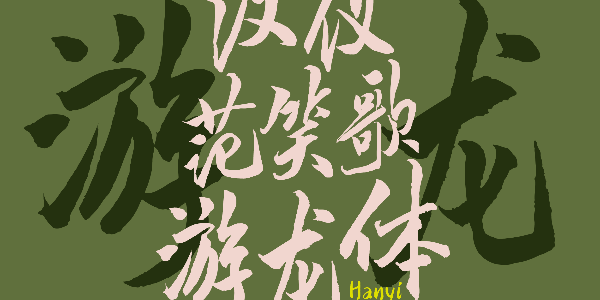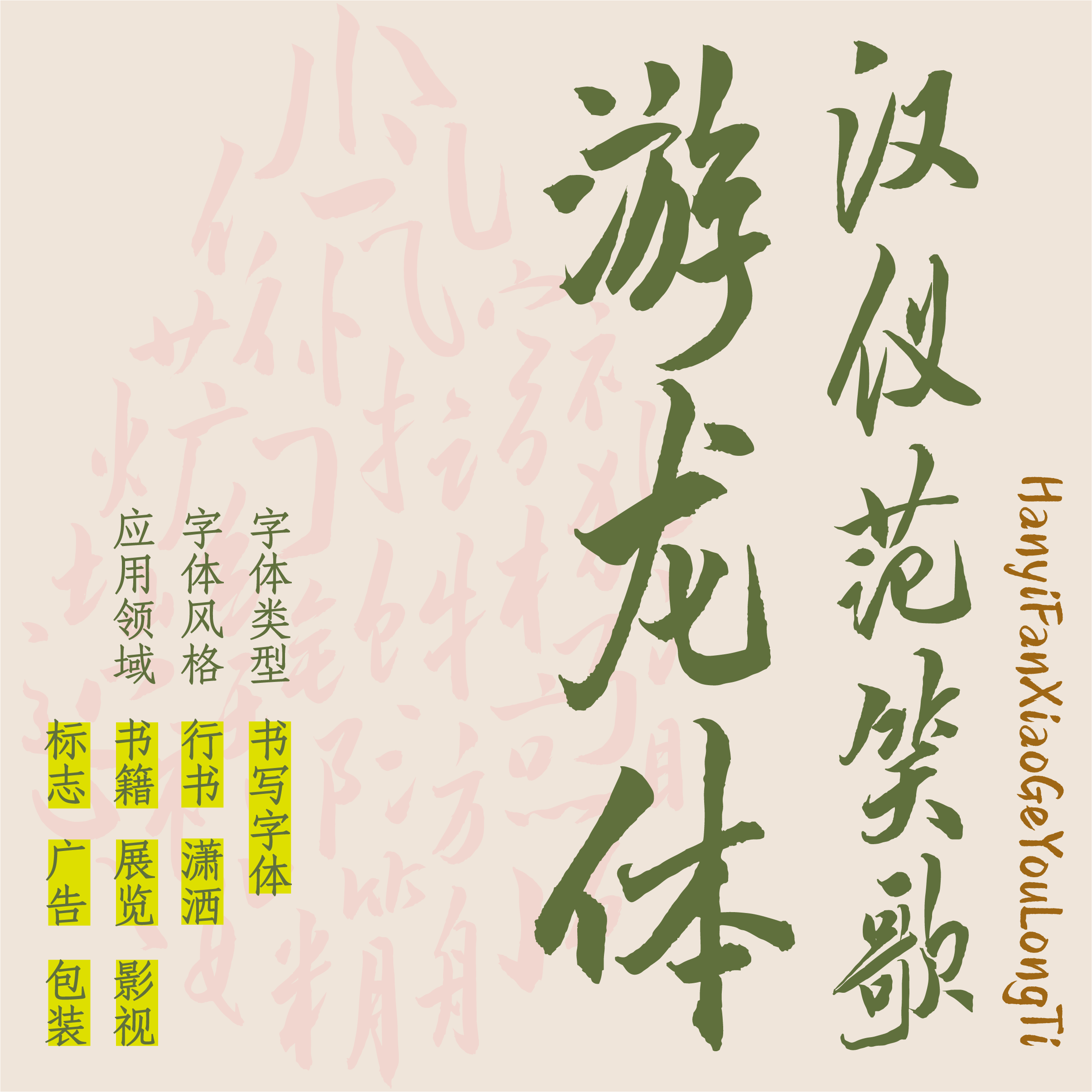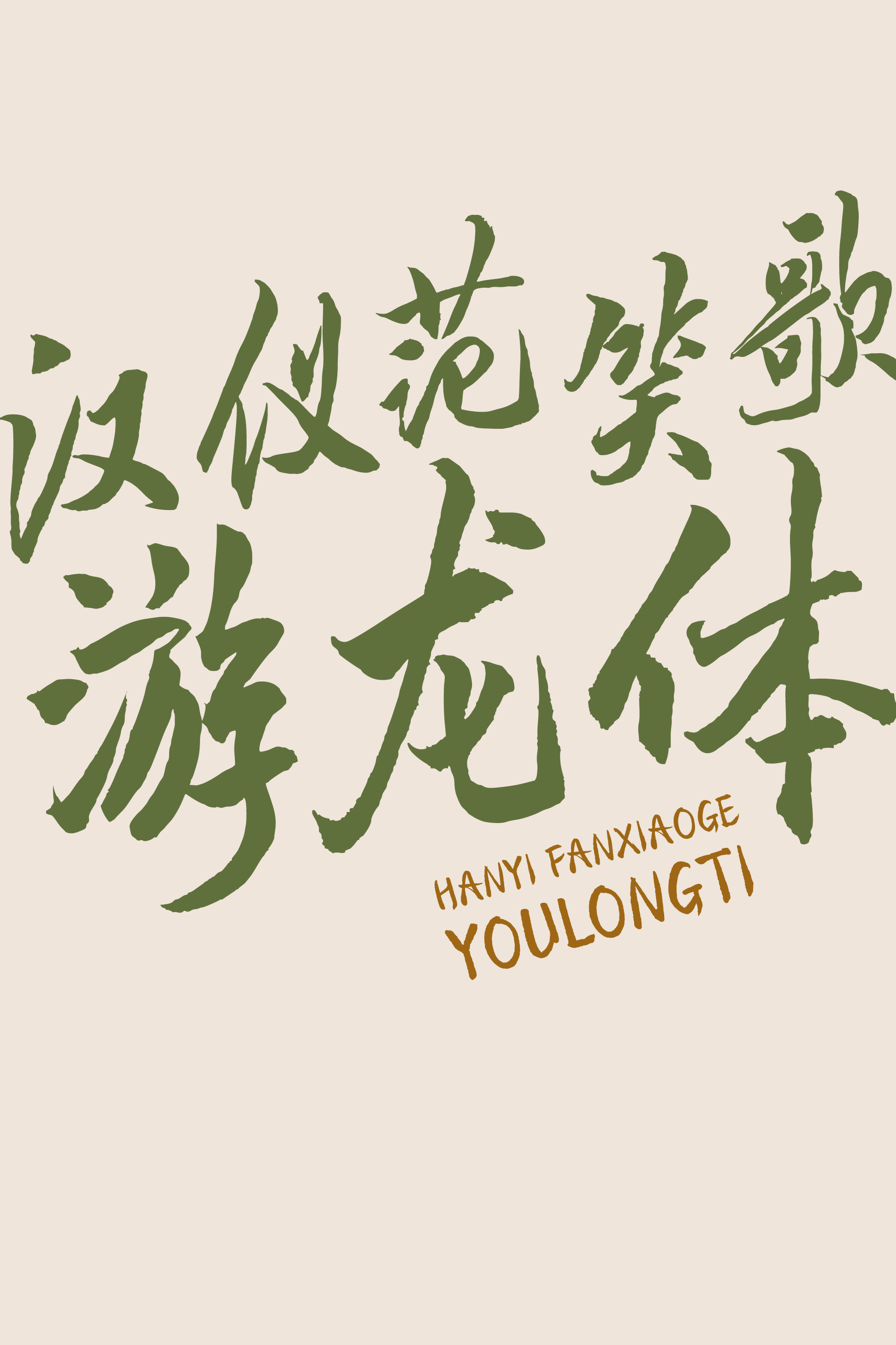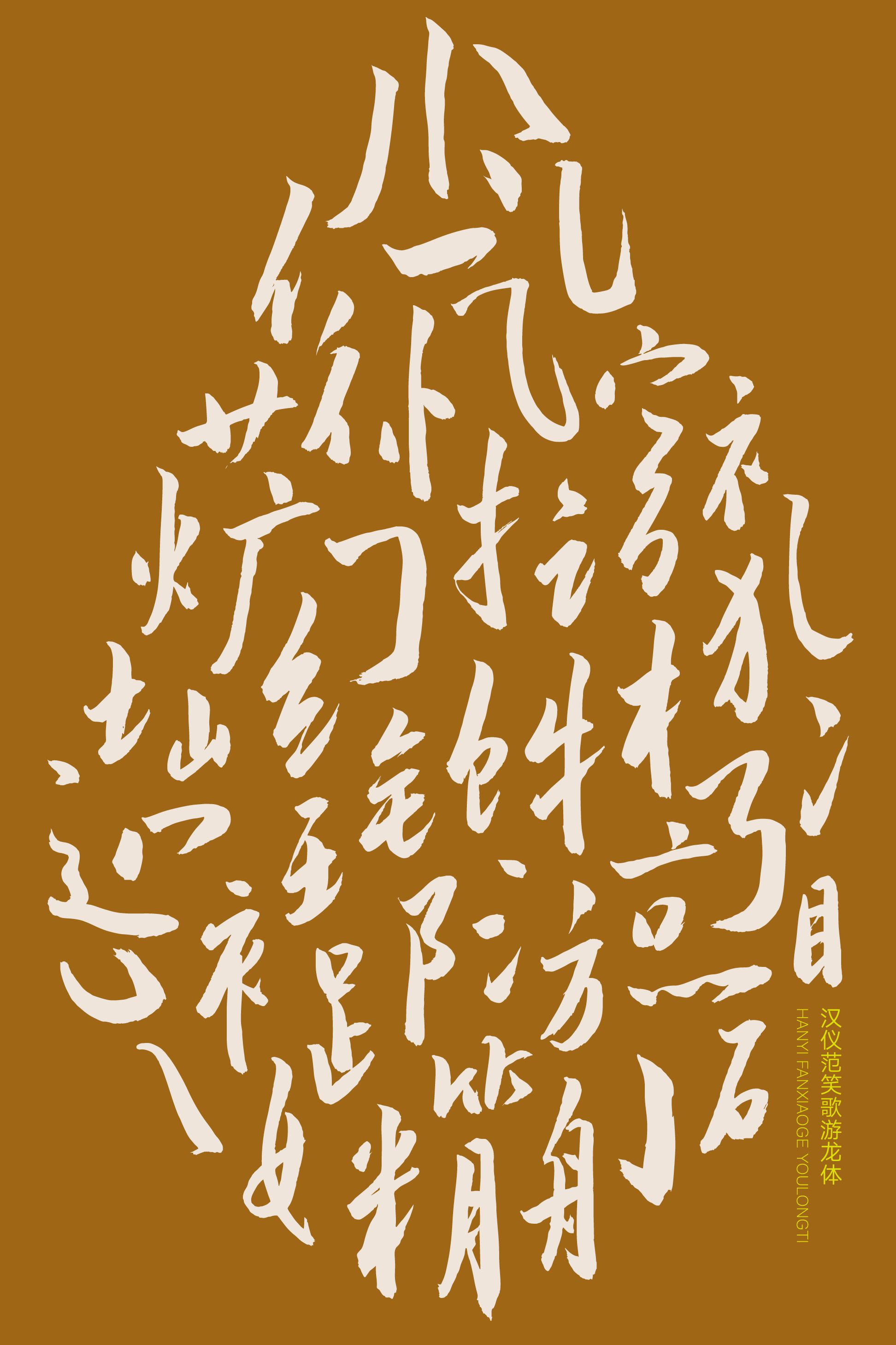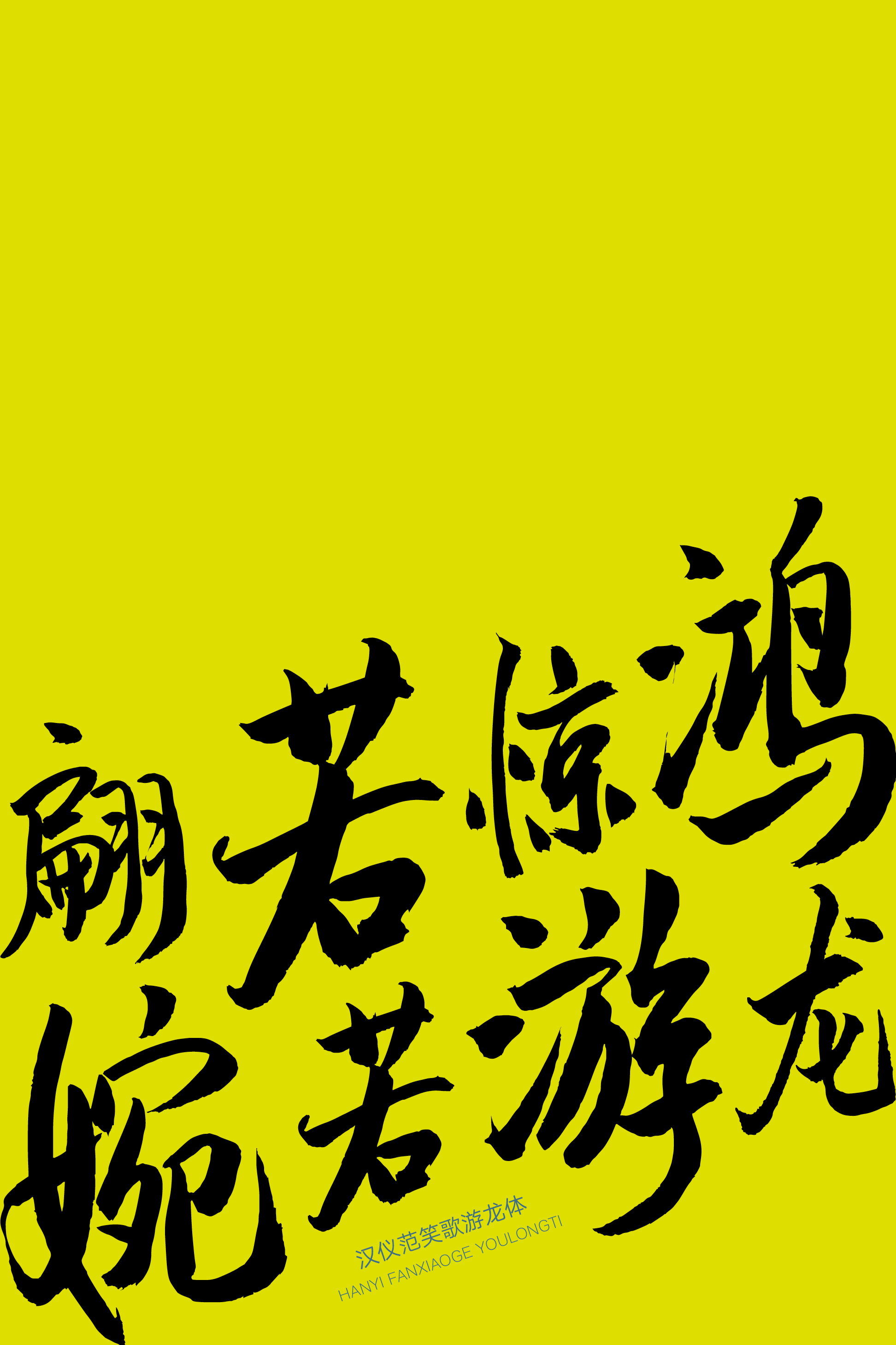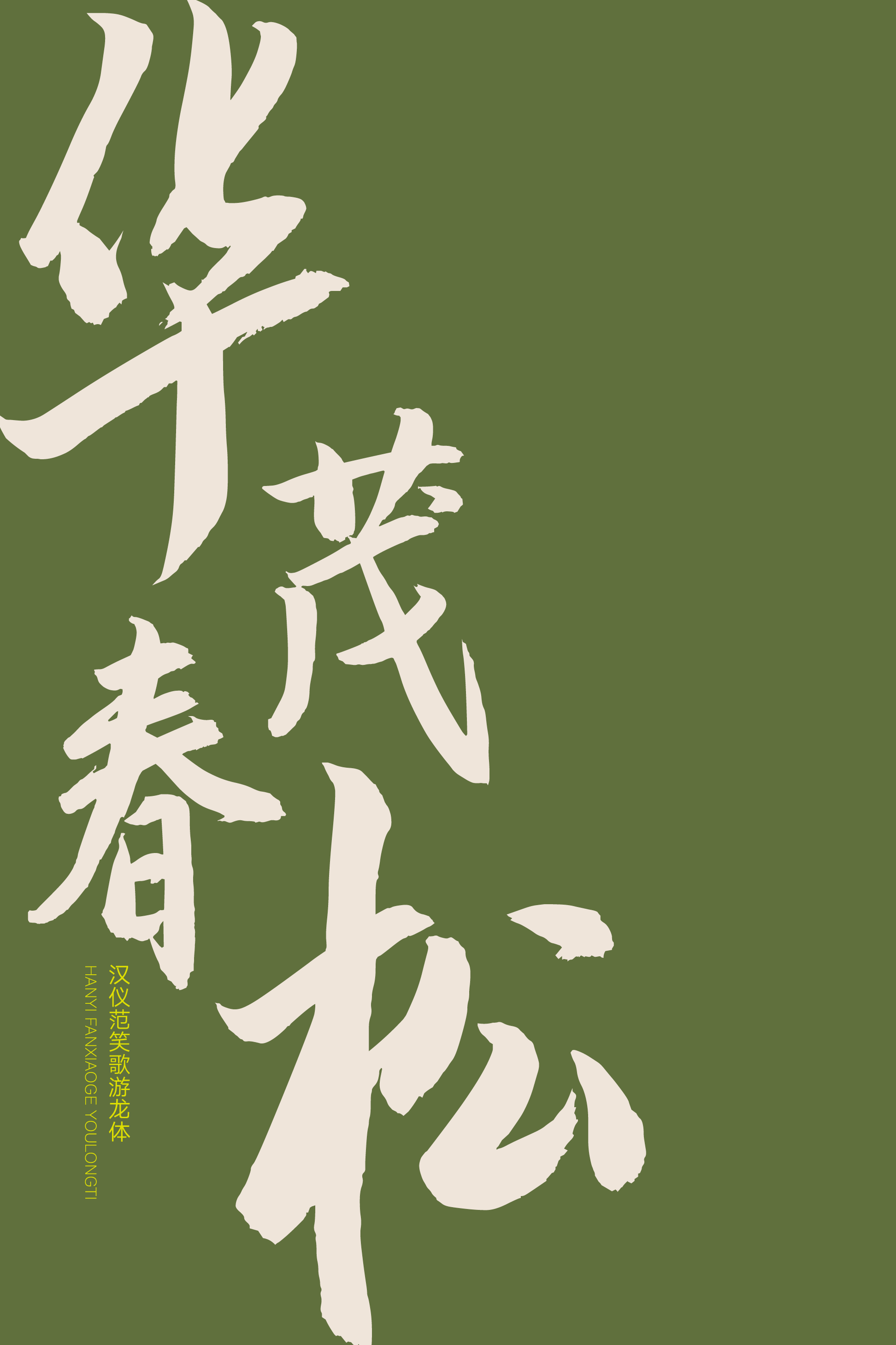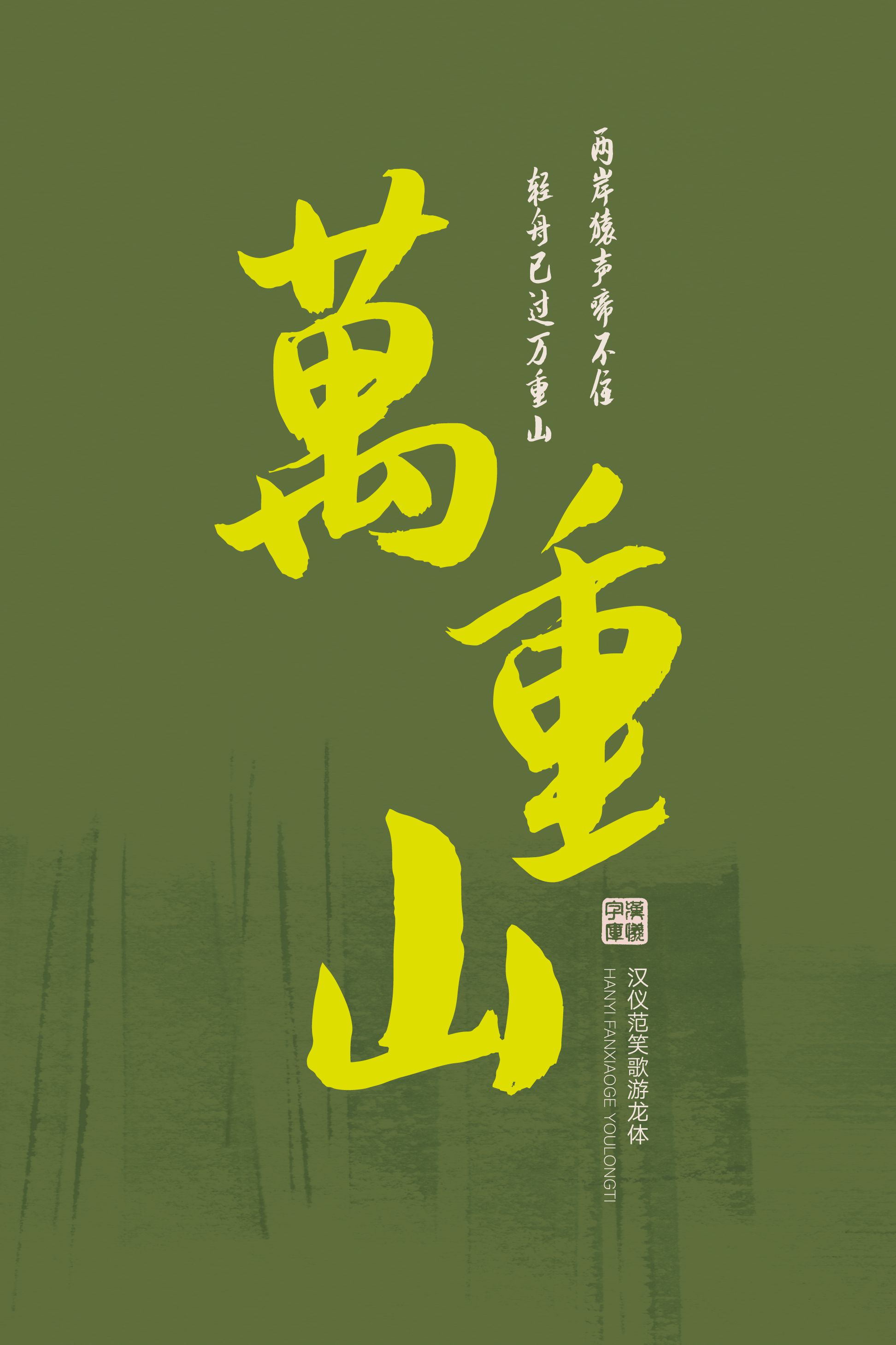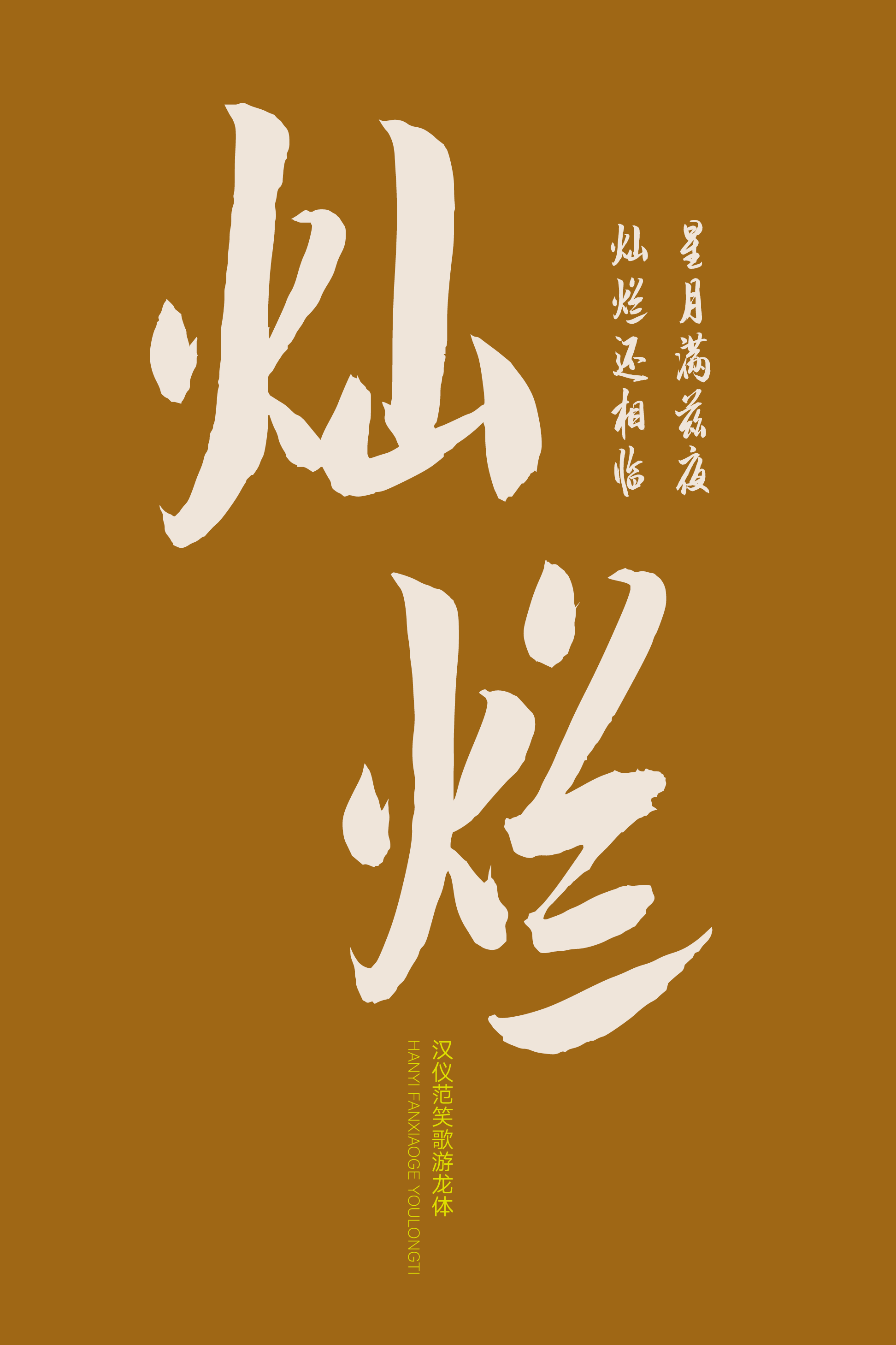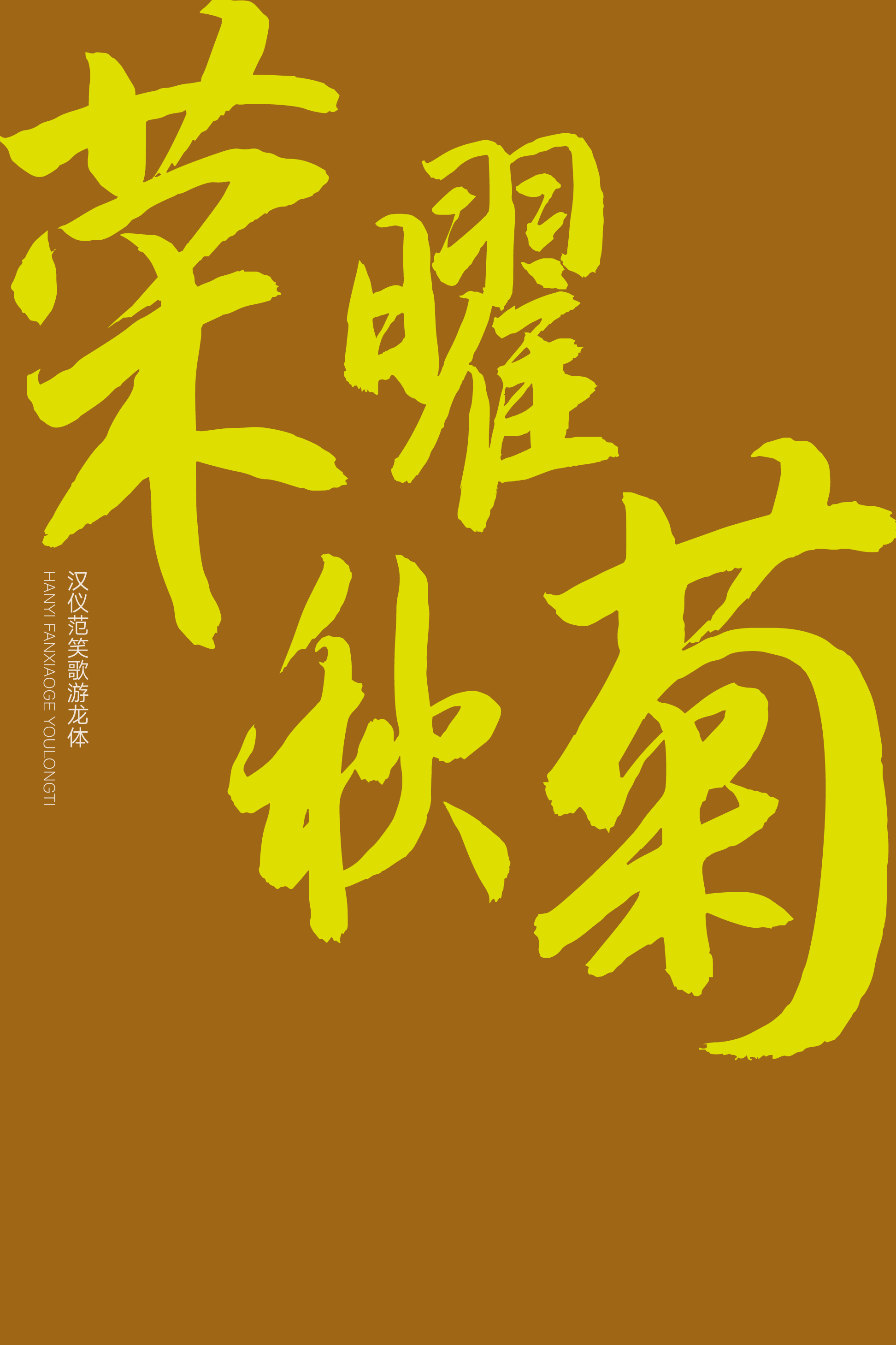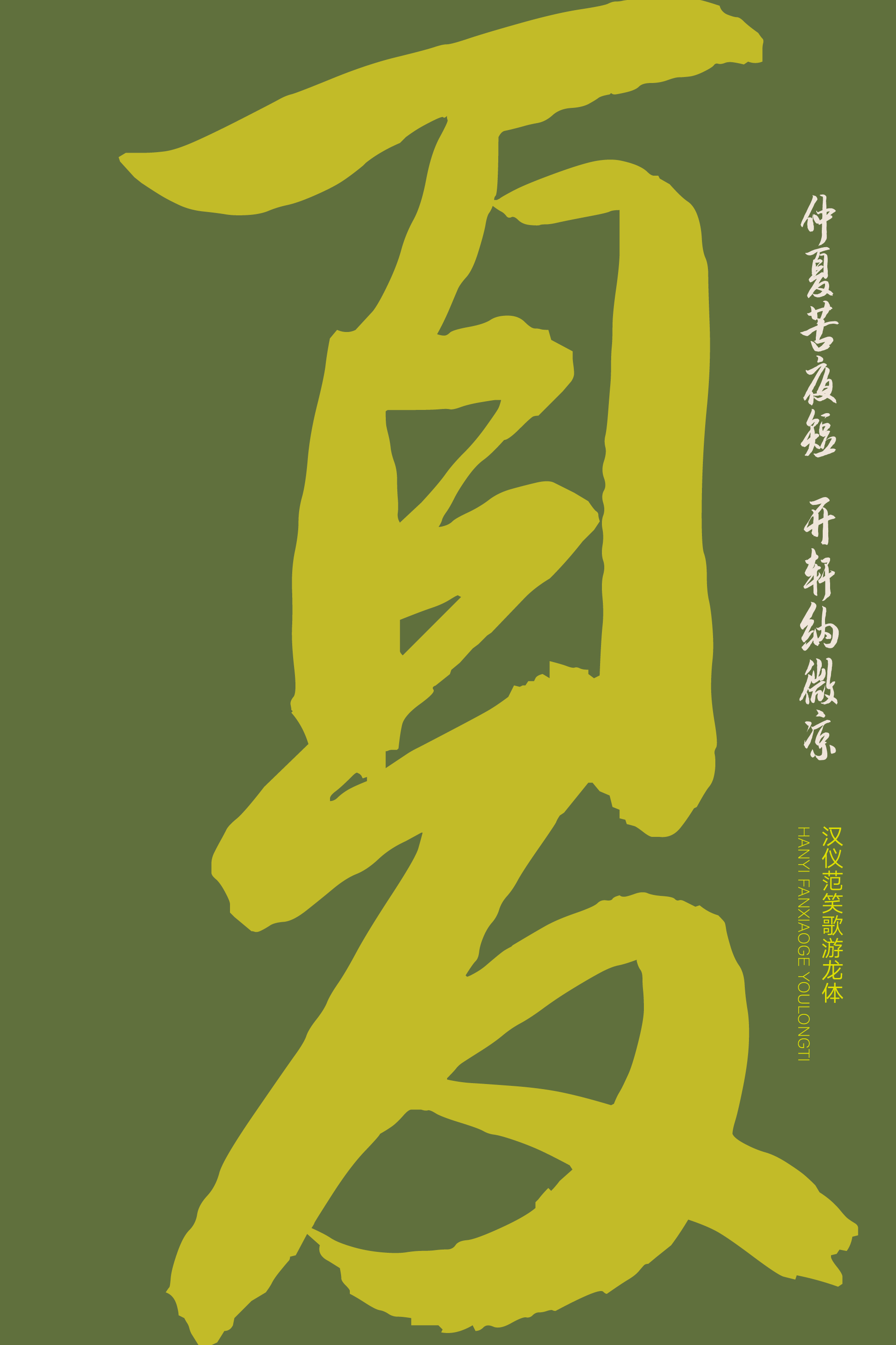
汉仪范笑歌游龙体
汉仪范笑歌游龙体,自由舒展、蜿蜒潇洒,宛若游龙,是一款雅俗共赏的行书风格书法字体,兼顾艺术性与实用性。整体字形瘦劲而挺拔,字势倾斜向上,笔意率性,线条流畅,在书写上借鉴了米芾书法的特征。这款字体适合用作标题排版或较短文本排版,如点睛之笔,增添潇洒气韵。在传统、古典的使用场景中,和谐而不突兀,同时融入了新鲜的视觉感受;在现代、潮流的使用场景中,渲染了快意与洒脱,又体现书写之传承。
整体字形瘦劲而挺拔,字势倾斜向上。
有如游龙向天而行,优美、洒脱。
笔意率性,线条流畅。
潇洒写就的西文部分亦如蛟龙直上。